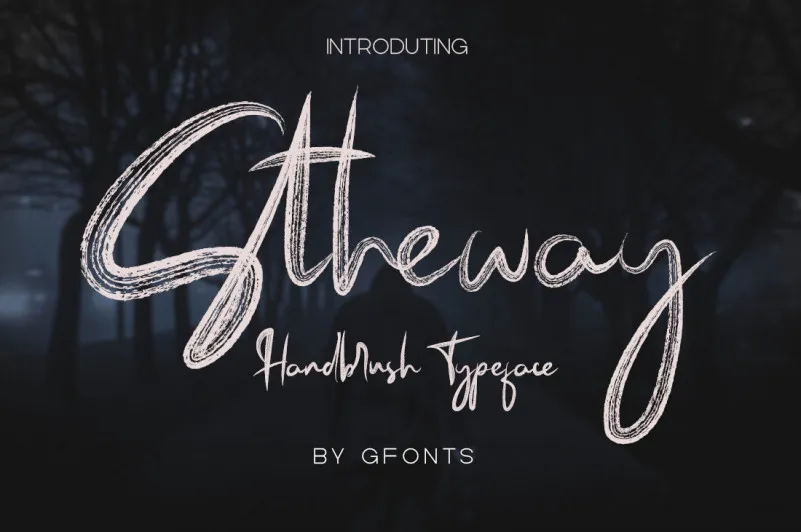
Stheway Brush Font – Download Grátis
Aqui está uma breve descrição para a página de download da fonte “Stheway Brush Font”, com um tom informativo e convidativo: Introduzimos Stheway Handwritten Font, uma fonte Hanwritten que traz à tona um estilo autêntico e um toque desafiador. Criada através do traçado manual em papel usando um pincel de tipo grosso, a fonte resulta em textura consistente. Esta novidade da Gfont oferece aos designers uma escolha fascinante para trabalhos que exigem uma personalização natural e sofisticada. Com Stheway Brush Font, você pode trazer uma vibe única e moderna a qualquer projeto gráfico, seja ele um website ou material de marketing impresso. Suas linhas suaves e detalhes distintos permitem um toque autêntico que se destacará em sua identidade visual. Adquira Stheway Brush Font agora e deixe seu trabalho soar único.